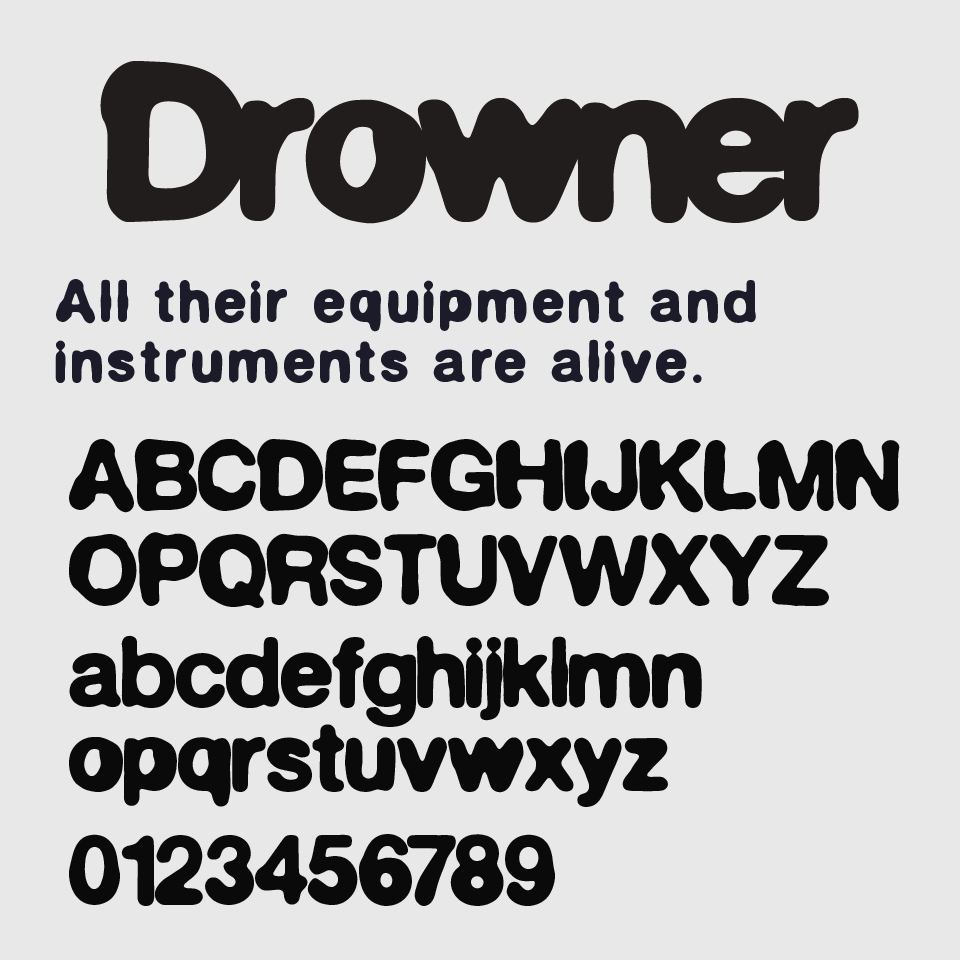
Drownerフォントは、インクが滲んだような質感とと太さを合わせ持つユニークなフォントです。
モコモコとした曲線が特徴的で、どの文字にも有機的な柔らかさがあります。黒の面積が大きく、どっしりとした印象を与えながらも、愛嬌とカッコよさがあるストリートな雰囲気があるデザインです。
ポップさとクラフト感を両立しており、ZINEやカジュアルなグッズデザイン、MVやジャケットのタイポグラフィにおすすめです。文字そのものにキャラクター性があるため、テキストを並べるだけでビジュアルとしての存在感を放つフォントです。